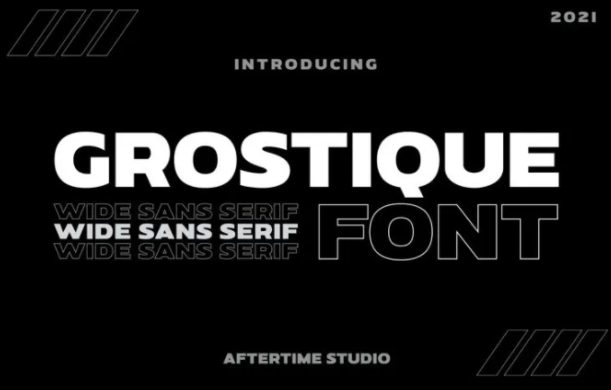
[Fontbundles] Grostique Font (2021)
Fontbundles Grostique Font (2021)
Шрифт Grostique идеально подходит для ваших будущих проектов.
Например, дизайн уличной одежды, брендинг логотипа, редакционный дизайн, брендинг, музыкальный плакат, дизайн веб-сайта, дизайн современной рекламы, цитата на плакате, название книги/обложки, специальные мероприятия и многое другое.